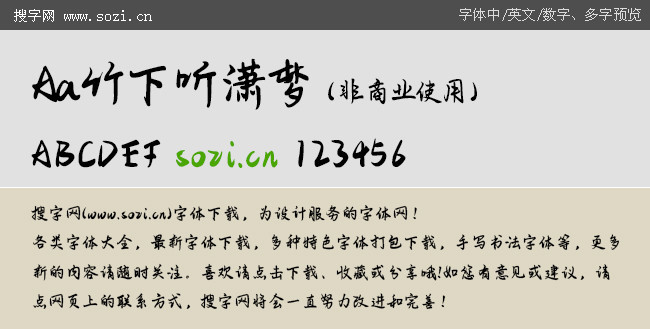
Aa竹下聽瀟夢(mèng)(非商業(yè)使用)
搜字網(wǎng)給大家提供一款A(yù)a竹下聽瀟夢(mèng)(非商業(yè)使用)中文字體下載,該字體是一款手寫中文字體,這款字體端莊,書寫簡(jiǎn)潔大方,適合包裝設(shè)計(jì)、書裝設(shè)計(jì)、海報(bào)設(shè)計(jì)等應(yīng)用(此字體為個(gè)人非商用版,商用可以聯(lián)系QQ:1006760504)。